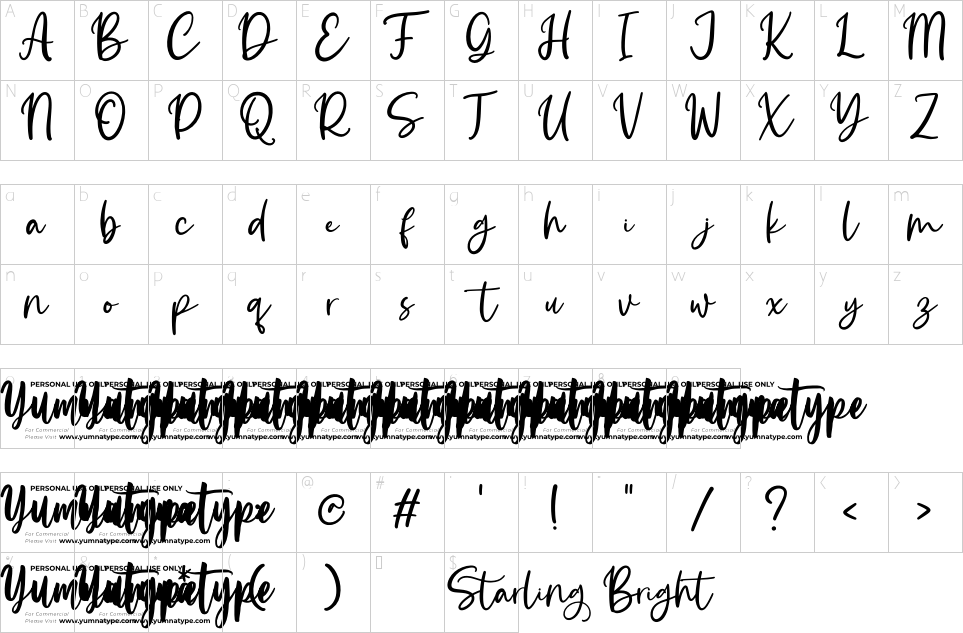
Descubra a beleza única da Starling Bright Font para seus projetos digitais com uma elegância clara e moderna. Desenvolvida pela Yumna Type, esta fonte oferece um toque fresco que enriquecerá seu design gráfico de maneira impressionante. Com sua simplicidade, a Starling Bright é perfeita para criações simples e intuitivas, ou pode ser usada em aplicações mais elaboradas para dar uma pitada sofisticada ao seu layout. Esta fonte foi baixada mais de 11 mil vezes por usuários que buscam qualidade e design único. Com um design limpo e moderno, a Starling Bright se destaca como uma excelente opção para quem está procurando uma fonte gratuita que não compromete em termos de estética ou funcionalidade. Seja você designer gráfico profissional ou iniciante, a Starling Bright pode ser o elemento diferenciador para seu próximo projeto.